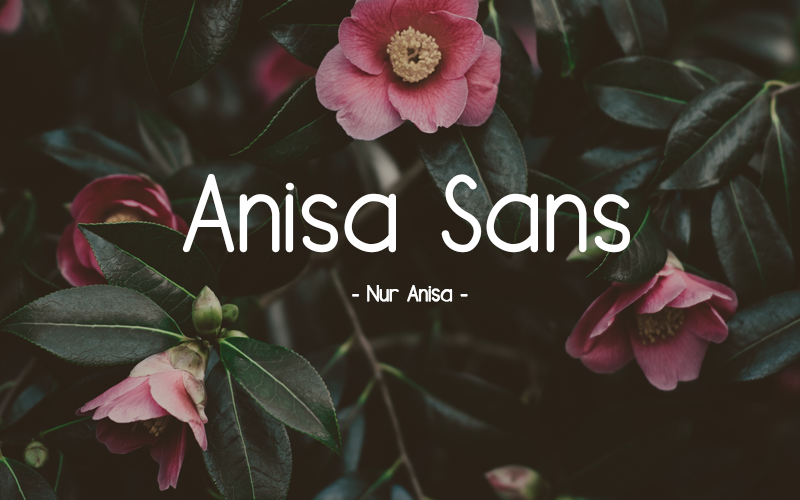
Anisa Sans Serif Font – Download Grátis
Olá designers, aqui está uma fonte serifless para vocês introduzir a todos os membros da comunidade. Introduzo a vocês a ‘Anisa Sans Serif Font’, um desenho elaborado à mão pela designer Hamilton. Anisa é uma fonte serifless de letra cuidadosamente projetada e compartilhada pelo letterhend, um design de tipo com acabamentos limpos e atraentes. Através de Anisa, seus trabalhos ou criações podem ser transformados em belíssimas histórias dos quais sempre sonhou. É perfeitamente adequada para criar aquela elegância necessária para materiais de casamento, revistas ou qualquer outro tipo de arte e design que possa precisar desta qualidade.